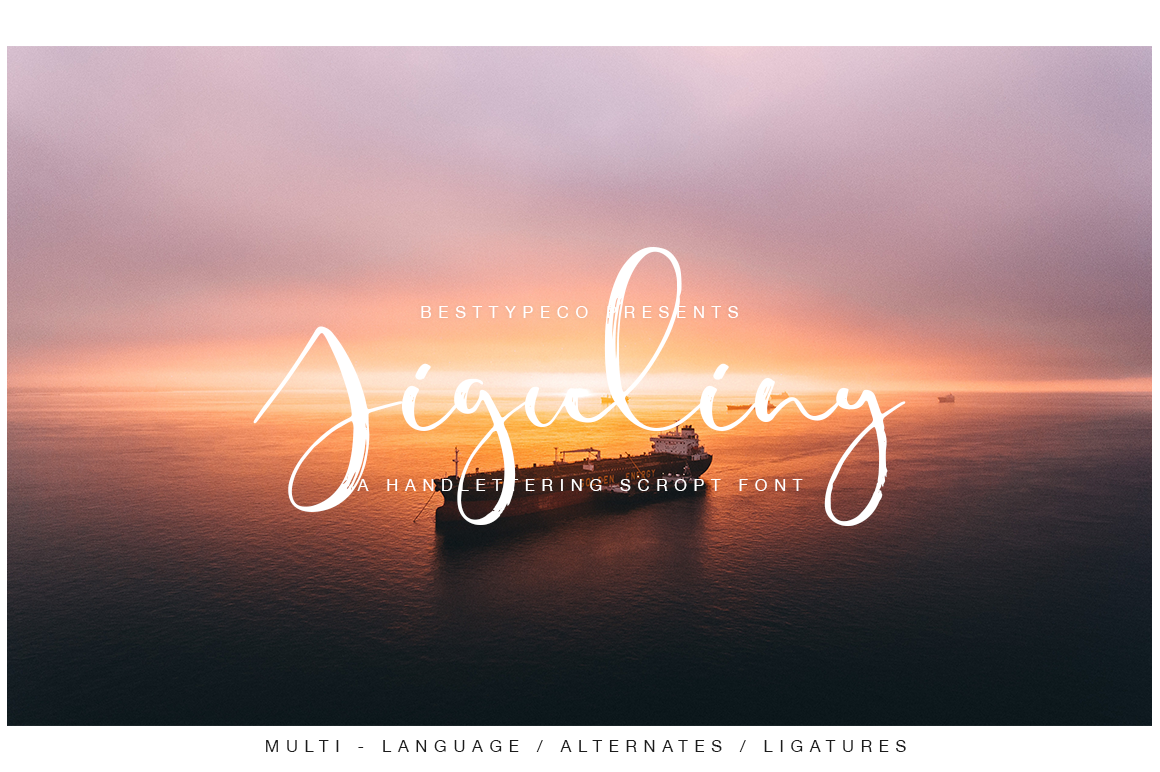
Jiguliny Script Font – Download Grátis
Jiguliny é uma nova fonte de escrita manuscrita com apelo moderno, ideal para designers que buscam uma opção única e criativa para seu trabalho. Esta fonte tem um toque fresco e versátil, projetada especialmente para aplicativos como cartões de aniversário, materiais de marca, cartões de convite, postais, logotipos pessoais, blogs, material de escrita profissional, revistas e mais. Jiguliny é perfeitamente adaptável a vários tipos de design gráfico, desde cartas de casamento até logotipos personalizados que destacam sua singularidade. A elegância natural da fonte cria um estilo único capaz de diferenciar seu trabalho entre outros designers. Seja você um artista digital em busca de uma nova maneira de expressar suas ideias ou um designer profissional buscando adicionar um toque único a seu material, Jiguliny é a escolha perfeita para criar designs únicos e memoráveis.